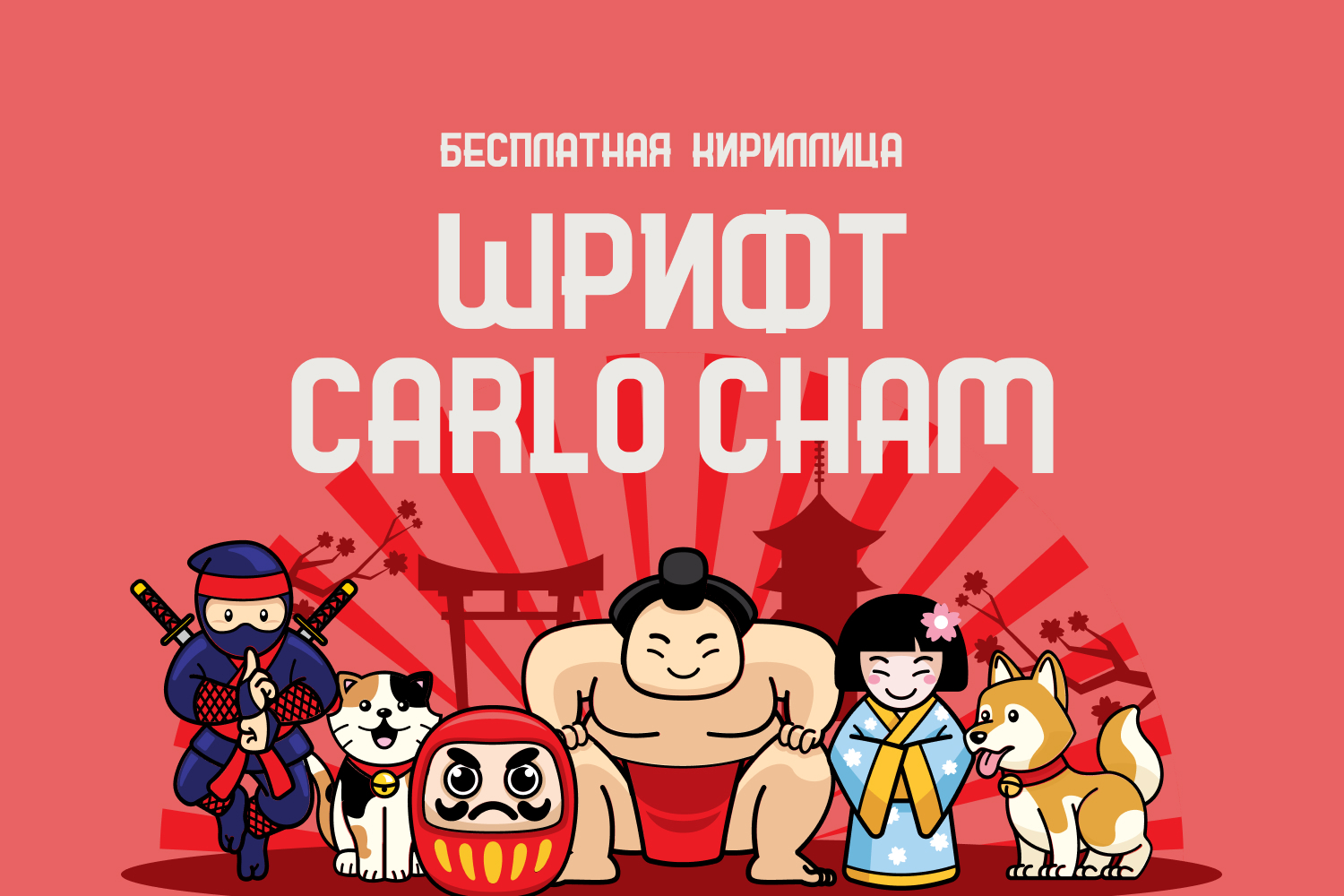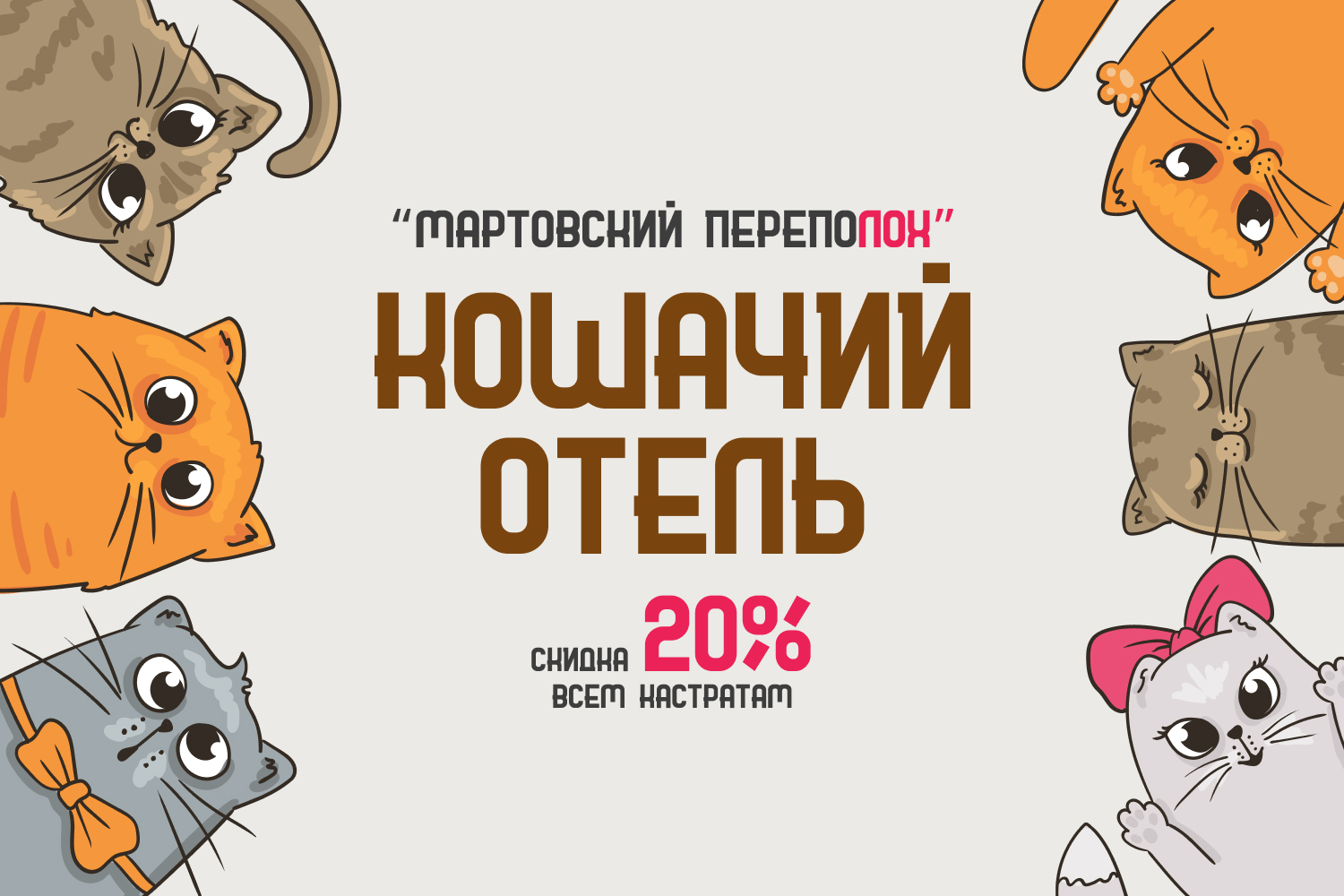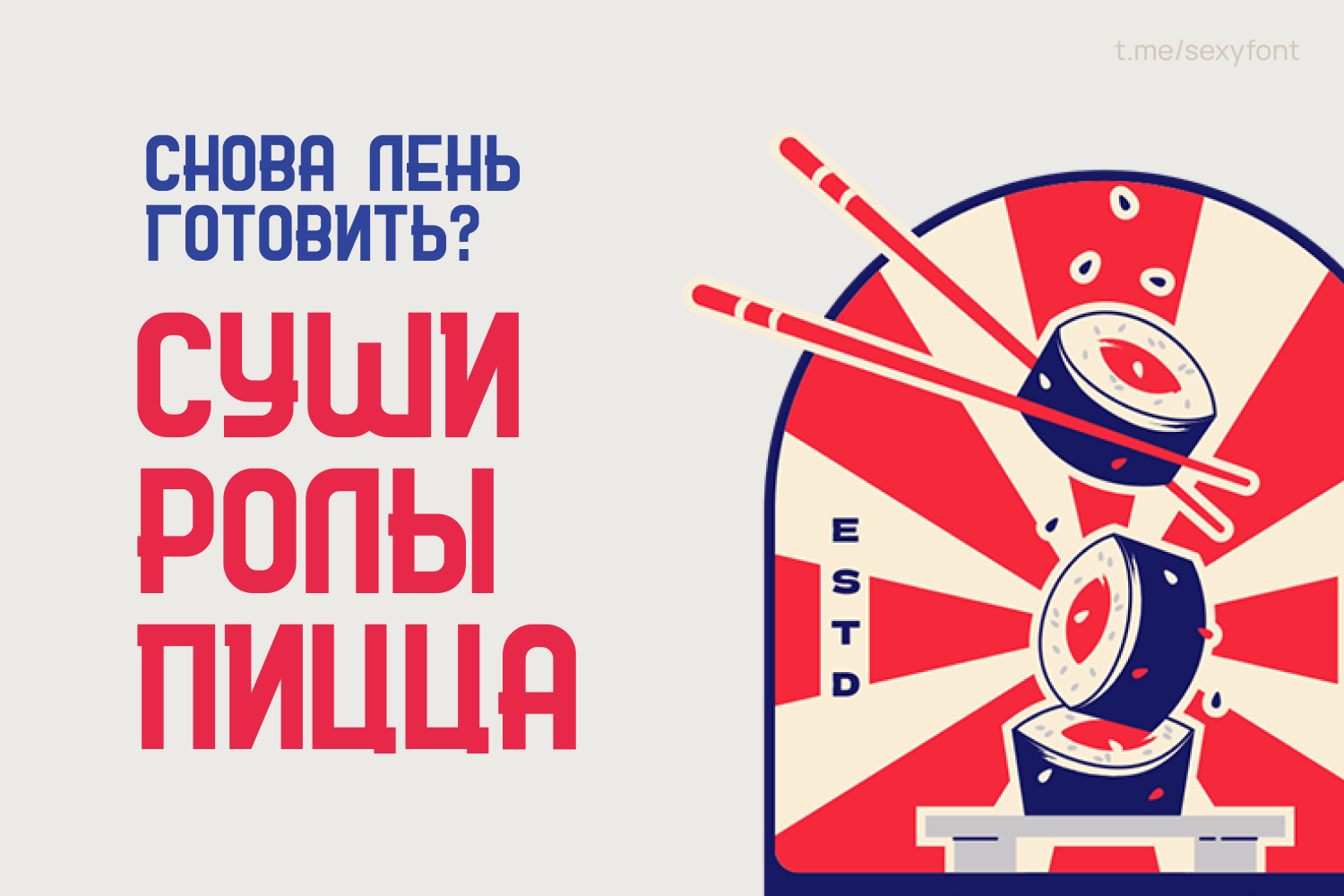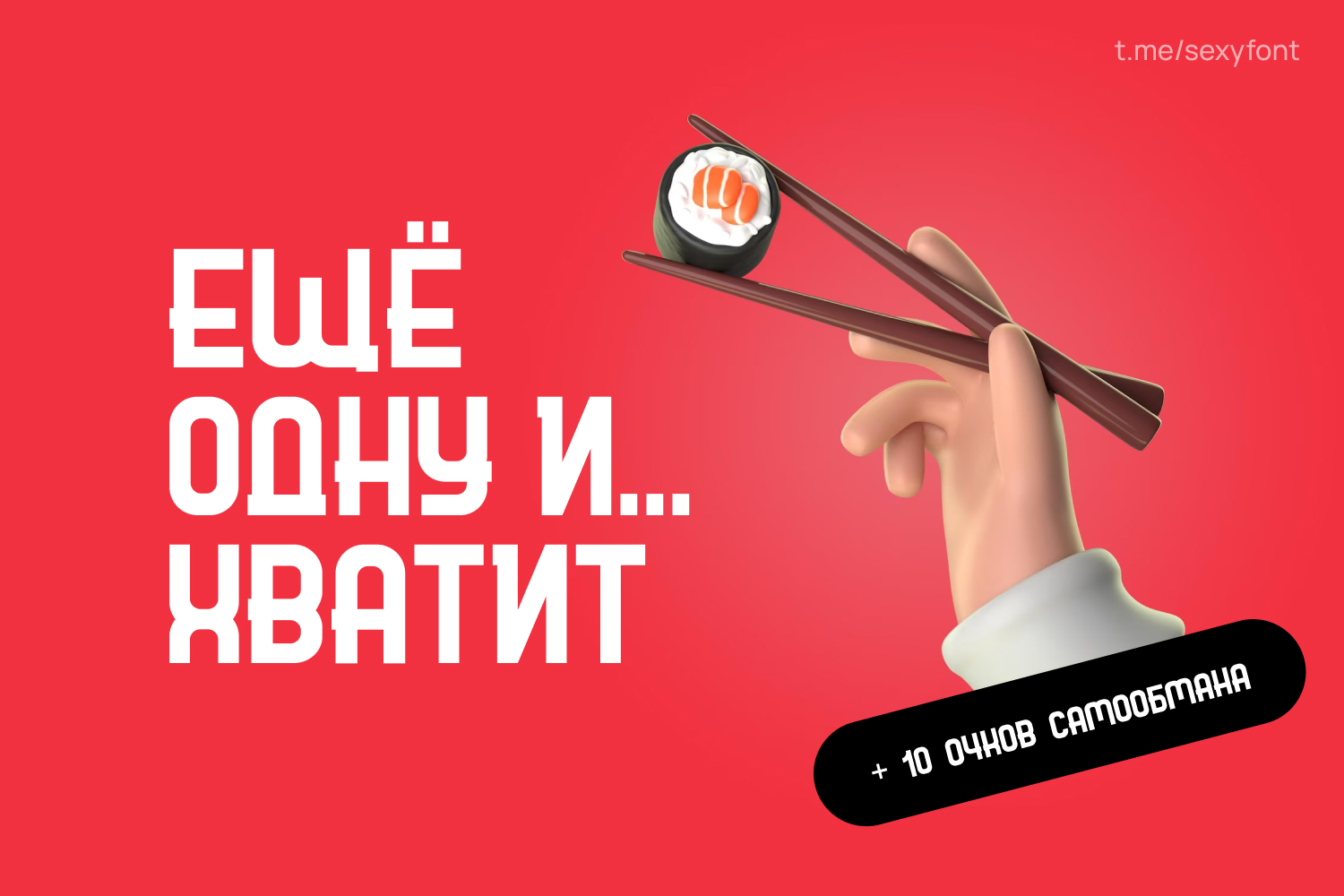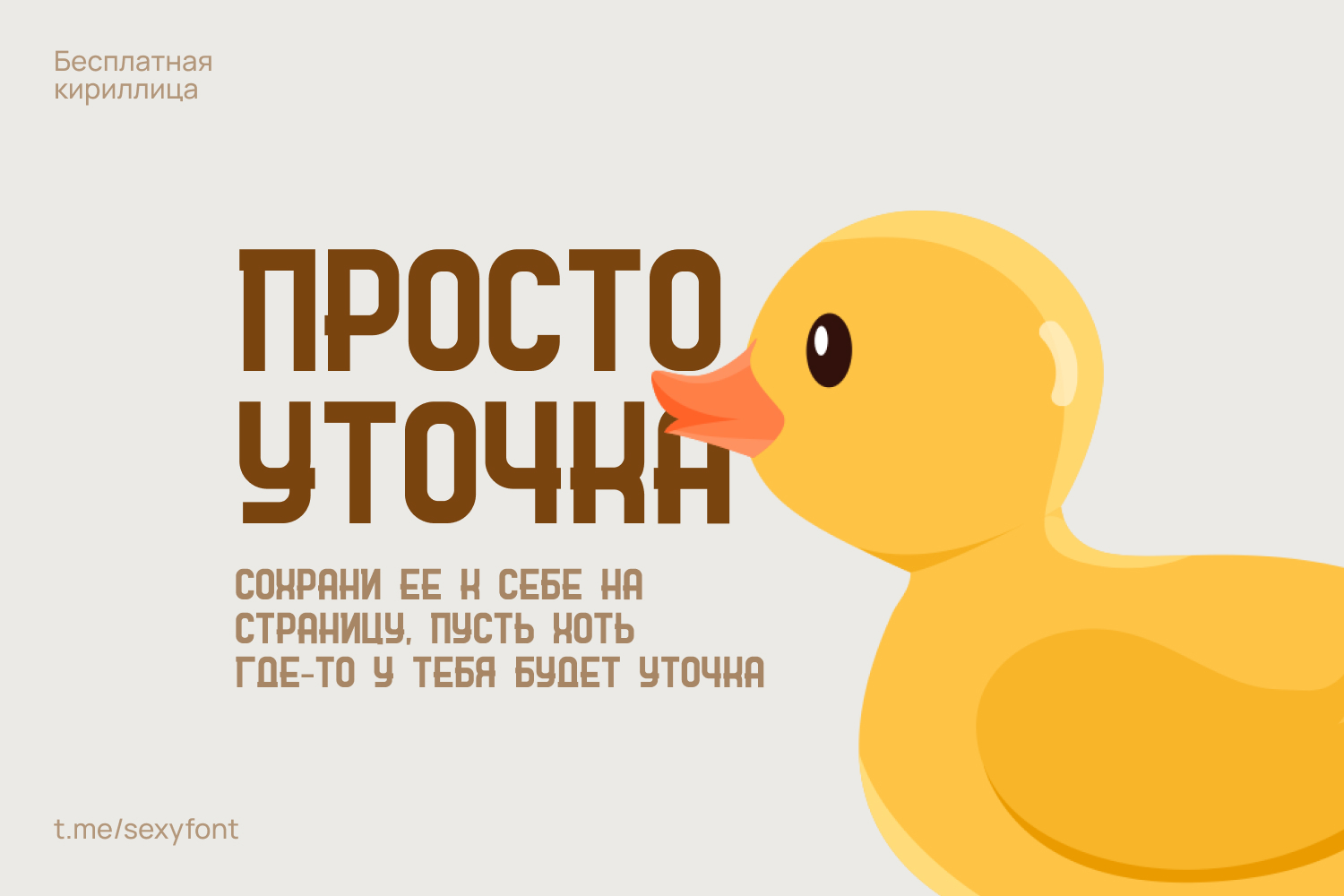
Шрифт Carlo Cham. Кириллица
Этот шрифт уже как-то выходил, но в другой презентации. Я решил сделать свой вариант. Заметил, что часто понимаешь, что шрифт тебе пригодится именно по презентации. Идеальный для тематик связанных с кафешками, едой и всяким прочим. Автор: Sergey Vasenin